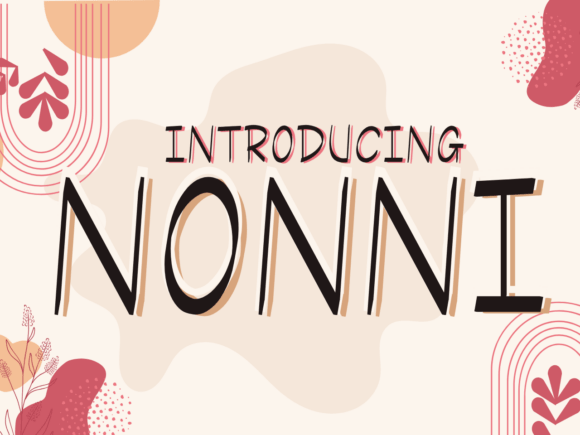
Love the Fonts
Việc tìm kiếm các thành phần thiết kế phù hợp có thể là một thách thức, nhưng Love the Fonts cung cấp một bộ sưu tập đặc biệt giúp nâng tầm công việc của bạn ngay lập tức.
Được chế tác với độ chính xác cao, Love the Fonts cung cấp các vector sạch, kiểu chữ mượt mà và giấy phép thương mại để bạn yên tâm.
Cho dù bạn đang tạo sản phẩm POD (In theo yêu cầu), thiệp mời đám cưới hay đồ họa mạng xã hội, Love the Fonts đều là một sự lựa chọn lý tưởng.
Mẹo chuyên gia: Kết hợp các yếu tố này với các phông chữ bổ sung để tạo ra các thiết kế độc đáo, bắt mắt nổi bật trên thị trường.